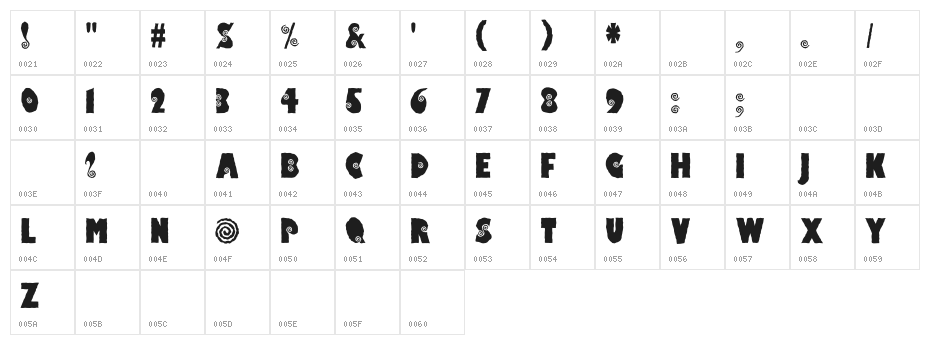
HippoCritic Font
| Stile generale | Playful, Whimsical, Artistic |
| Progetti proposti | Ideal for children's book covers, playful branding, party invitations, and creative posters. |